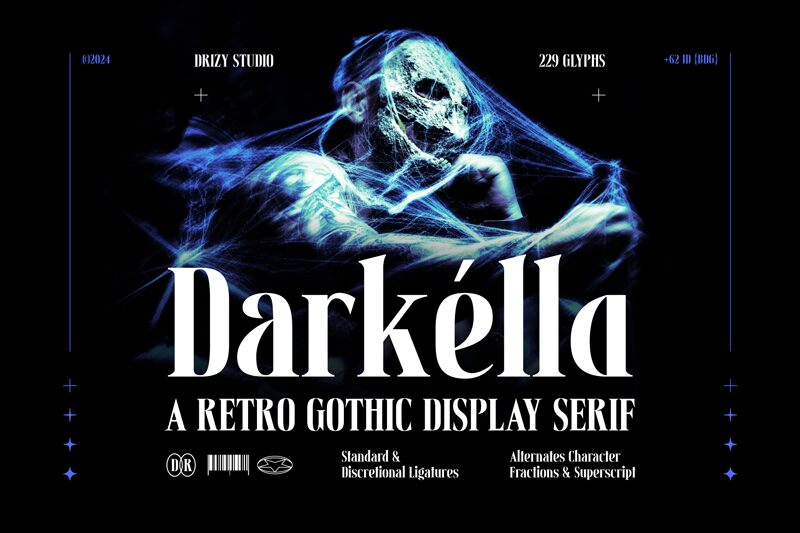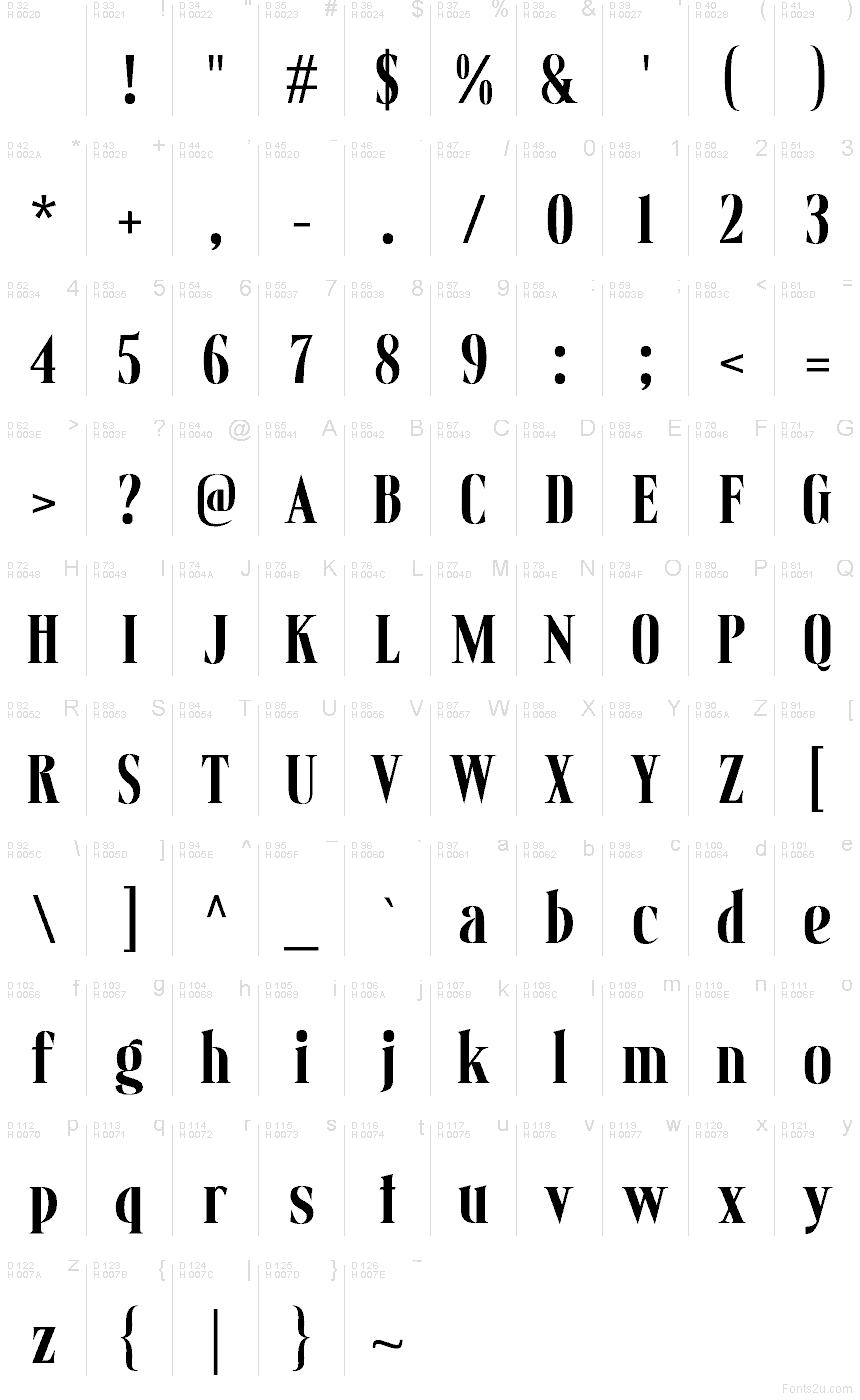
Darkella, realizzata da Drizy Studio, è un font display serif retrò gratuito, caratterizzato da un mood raffinato e alla moda. Le lettere combinano un netto contrasto con curve morbide e leggermente drammatiche; il risultato è un font elegante ma non rigido, con una silhouette slanciata e dettagli incisivi che evitano qualsiasi effetto di classicità banale.
È ideale per il branding, il packaging di boutique, testate di riviste, poster e copertine dove serve un font gratuito che aggiunga un tocco d'epoca ricercato senza risultare polveroso. Usalo per titoli brevi, scritte a effetto o un logo distintivo, specialmente se vuoi far risaltare quel glamour vintage attraverso le sue curve sinuose e il ritmo stretto ad alto contrasto.